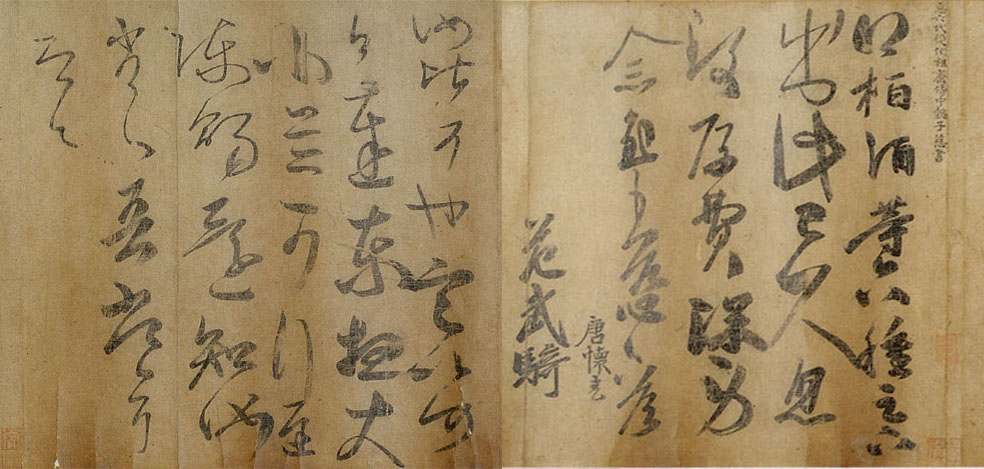
王慈
王慈简介
字伯宝,临沂(今山东临沂)人。僧虔子。少与从弟俭共学书。善隶,行书。王慈草书运笔圆浑,含蕴凝重,然体态十分灵动,纵横姿肆,使人联想到王献之书作风格。书作有《栢酒帖》、《尊体安和帖》等存世。 谢凤子超宗诣慈,慈正学书,未即放笔。超宗曰:“卿书何如虔公?”慈曰:“慈书比大人,如鸡之比凤。”超宗狼狈而退。卒年四十一。
王慈《栢酒》《汝比》帖 于辽宁省博物院藏的《唐摹万岁通天帖》
王慈《栢酒》《汝比》释文:
唐怀充,
臣六代从伯祖齐侍中懿子慈书
得栢酒等六种,足下
出此已久,忽
致厚费,深劳
念慰。王慈具答。
唐怀充,
范武骑。
汝比可也,定以何
日达东,想大
小并可行。迟
陈赐还。知汝
劣劣,吾常耳。即具。